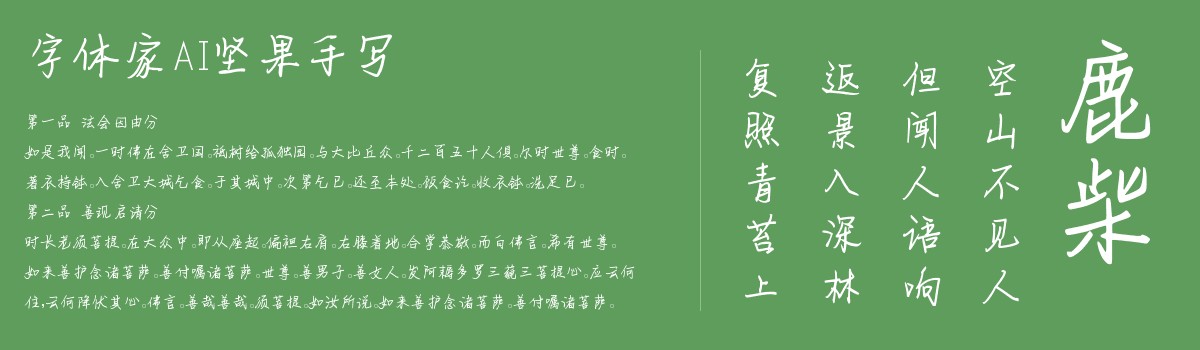
字体家AI坚果手写
字体家AI坚果手写是一款由字体家AI神笔造字生成的艺术字体,笔触带着手写的自然温度,线条并非机械般规整,起笔有轻微顿感,收笔带自然拖尾,像钢笔在纸上缓缓划过,留有手工书写的细微倾斜与不匀粗细。模拟墨色变化的柔和过渡,没有冰冷的统一感,每一笔都似带着书写者的独特印记,整体温暖而亲切,透着手写特有的随性与温度。适合用于一些广告标题、平面文案、海报标题、网页广告用字的编辑。